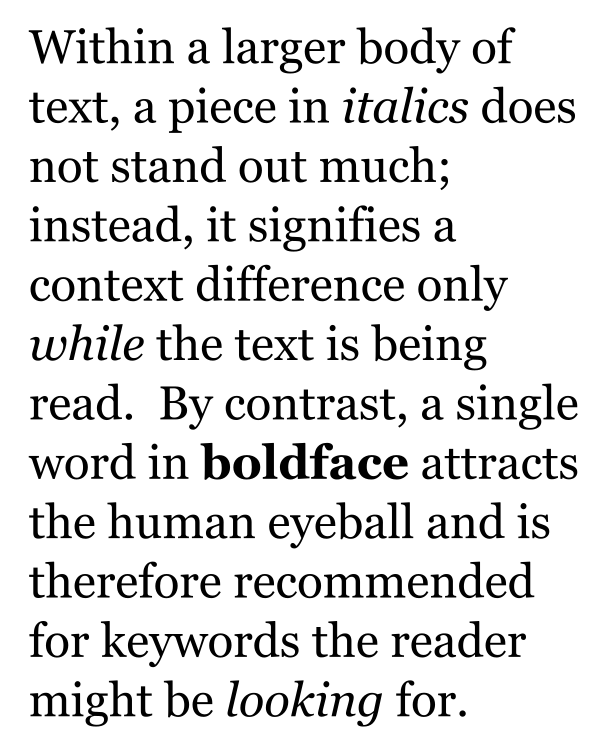
Жирный шрифт
Жирный шрифт (англ. bold) — одно из начертаний шрифта. Предназначено для выделения части текста или набора заголовков. Отличается большей насыщенностью линий в сравнении с основным начертанием[1].
«Практика показывает, что в текстовом шрифте для правильного выделения толщина основного штриха жирного начертания должна быть больше, чем у светлого, не менее чем на 25%. Первый жирный шрифт был создан около 1800 года лондонским словолитчиком Робертом Торном (англ. Robert Thorne, 1754—1820) как самостоятельный шрифт для набора афиш и плакатов, и только к концу XIX века жирные шрифты стали использоваться как выделительные»[2].